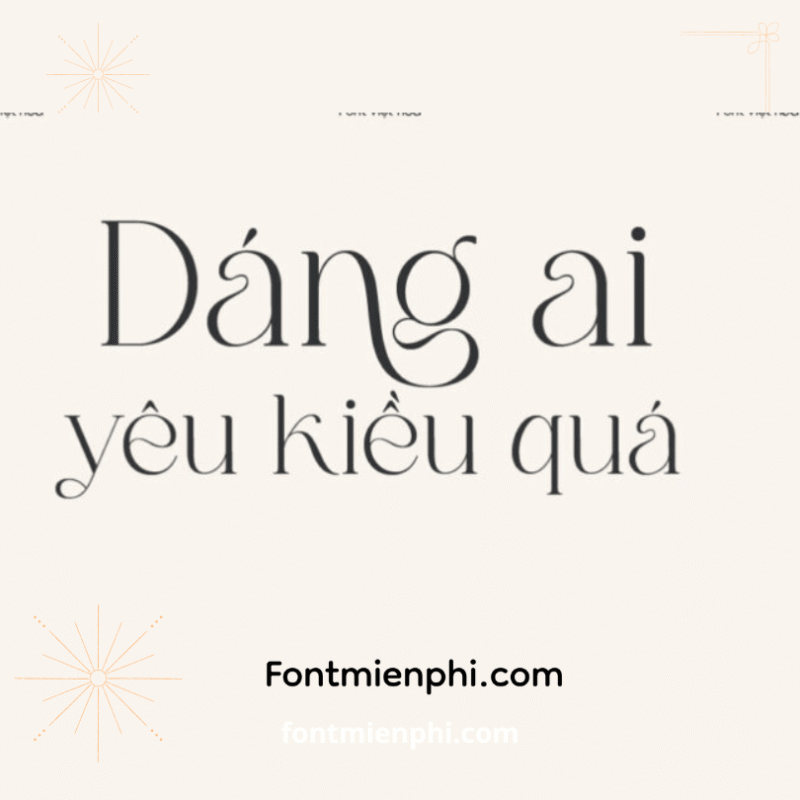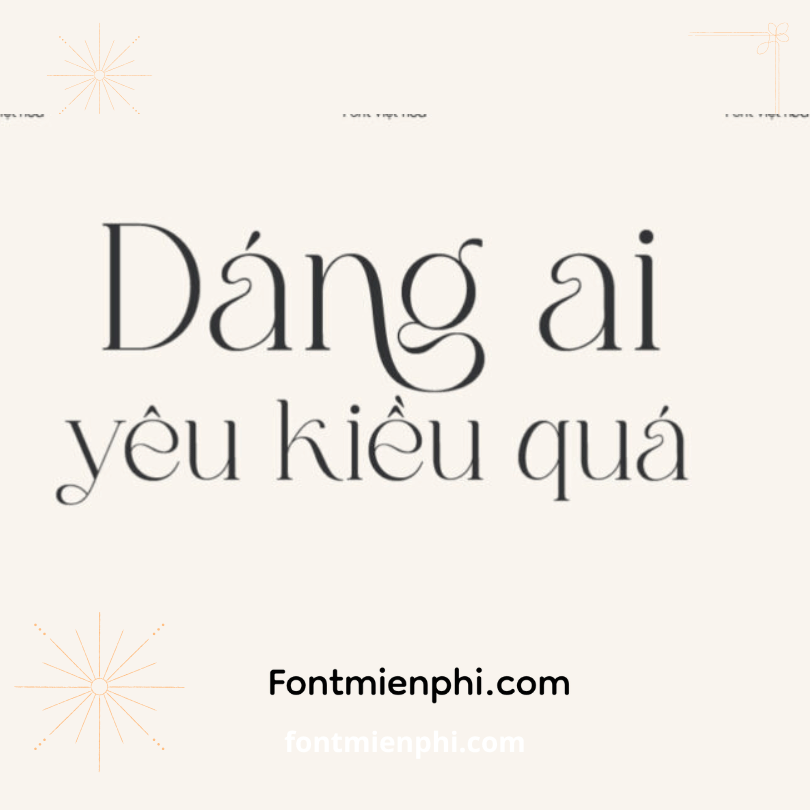
Font Việt hóa 1FTV VIP Stylish Mother
Font Việt hóa 1FTV VIP Stylish Mother – Giải Pháp Typography Chuyên Nghiệp Cho Thiết Kế Đỉnh Cao
1. Giới Thiệu
Font Việt Hóa 1FTV VIP Stylish Mother là bộ font chữ cao cấp, được thiết kế tỉ mỉ với phong cách sang trọng, phù hợp cho các dự án đòi hỏi tính thẩm mỹ và chuyên nghiệp. Với khả năng tương thích hoàn hảo với tiếng Việt, font chữ này trở thành lựa chọn hàng đầu cho designer, marketer, và các nhà sáng tạo nội dung.
2. Đặc Điểm Nổi Bật
✔ Hỗ Trợ Tiếng Việt Chuẩn: Đầy đủ dấu và ký tự đặc biệt, đảm bảo hiển thị rõ ràng, mượt mà trên mọi nền tảng.
✔ Phong Cách Độc Đáo: Nét chữ thanh lịch, kết hợp giữa hiện đại và cổ điển, phù hợp với đa dạng ngữ cảnh (logo, banner, typography nghệ thuật).
✔ Đa Dạng Ứng Dụng: Dùng cho in ấn, thiết kế đồ họa, quảng cáo, website, và các dự án sáng tạo khác.
3. Ưu Điểm Vượt Trội
• Chất Lượng VIP: Nét chữ sắc nét, không lỗi font khi in ấn hoặc hiển thị kỹ thuật số.
• Tính Linh Hoạt: Phù hợp với nhiều phong cách thiết kế từ tối giản đến cầu kỳ.